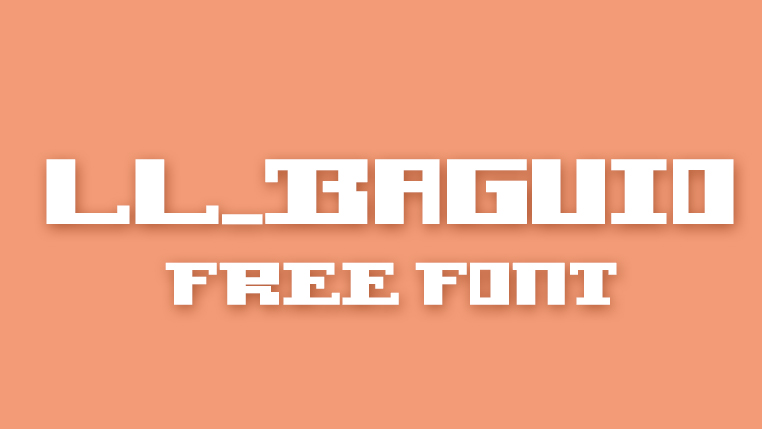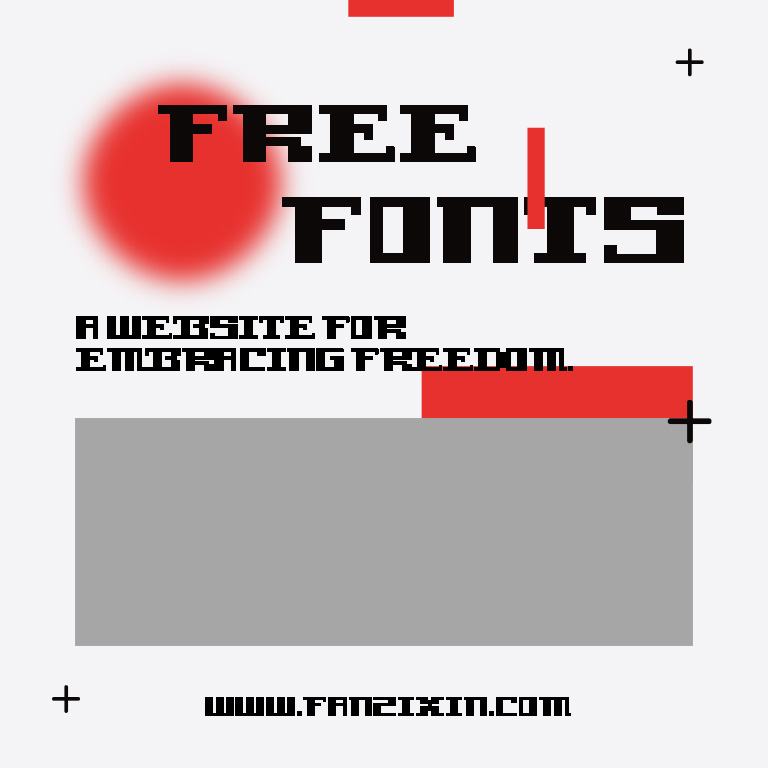
一款能把竹编的经纬感写进字母里的像素字体?LL Baguio 来自菲律宾,用它做标题,自带手工与科技碰撞的气质。
字体介绍
LL Baguio 是一款来自菲律宾的像素风格英文字体,创作者通过邮件确认这款字可以免费用于个人和商业用途,这一点在国内设计圈相当难得。它的灵感像是把像素块当成编织的经纬线,让每个字母都带着竹编、草编一类手作工艺的痕迹,同时又不失数字时代的电子科技感,民族美学与现代感在同一套字形里相遇,风格非常独特,在同类像素字体里显得格外出挑。
这款字体的字形并不追求完美对称,笔画粗细对比强烈,还带着些许不完美的有机笔触,正是这种粗犷感让它极具辨识度。无论是南洋主题展览、地方节庆物料,还是纪念品与手作布艺包装,它都能让设计多一层文化温度;旅游地图、观光介绍这类需要亲切氛围的版面,用它做标题也格外契合,很容易做出有人情味、有记忆点的视觉。
字形特点
像素织感:字母由像素般的几何块构成,像竹编草编的纹路一样错落交织,把民族工艺美学自然地融进数字字形,细看充满手作细节,远看又有科技感。
粗犷有机:笔触不追求绝对规整,字形略带不对称和手工痕迹,形成自然、朴拙而有力的视觉表情,让标题更有人情味,摆脱机械感。
粗细强对比:笔画粗细差异明显,视觉节奏感强,即使放大使用也依然站得住,非常适合担当版面的视觉焦点,做主打标题气势很足。
民族与科技:既有传统编织工艺的韵味,又带电子像素的现代气息,跨文化气质让设计不落俗套,应用场景灵活,从旅游文创到电子海报都能驾驭。
字重与字数
文章未说明字重数量,字体为全大写展示字体,使用时以标题和装饰性排字为主,适合大字场景,放得越大越有味道。
英文字体,字母以全大写形式呈现,适合英文标题与短句排版,具体字符范围以官方文件为准。
字体使用建议
这款字体在以下场景表现尤其出色:
- 文创与旅游品牌标识
- 地方节庆海报与观光地图
- 纪念品及手作布艺包装
- 南洋主题展览与书籍设计